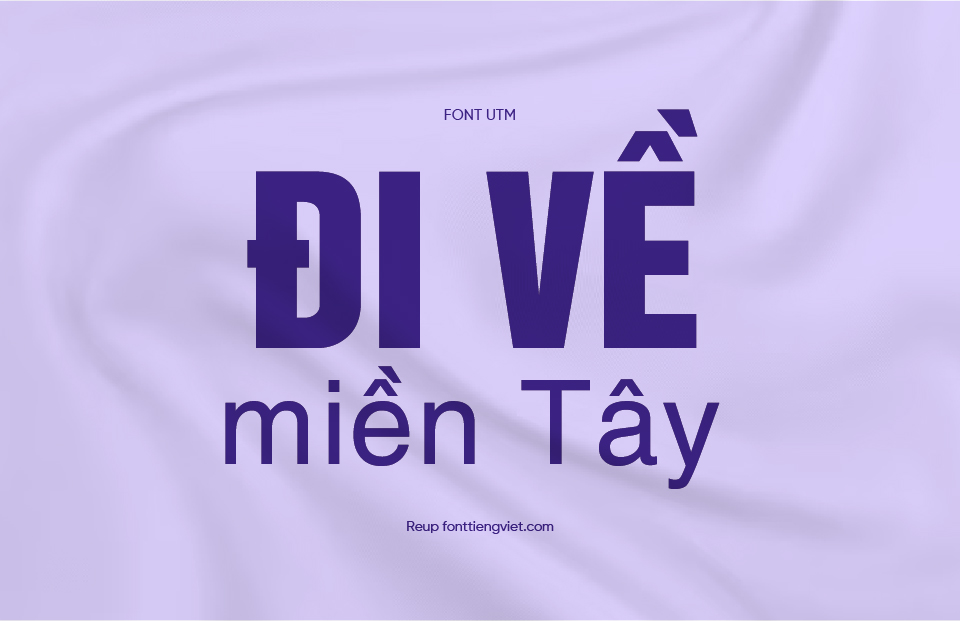
Trong thế giới thiết kế và typography, việc lựa chọn một Font Chữ chất lượng, dễ đọc và chuyên nghiệp luôn là ưu tiên hàng đầu, đặc biệt là đối với các bạn học sinh, sinh viên đang thực hiện đồ án, báo cáo hoặc chuẩn bị cho kỳ thi tốt nghiệp. Một trong những bộ font được cộng đồng thiết kế Việt Nam tin dùng nhất chính là Font Việt hóa UTM Helve. Đây không chỉ là một phông chữ đẹp mà còn là giải pháp hoàn hảo cho mọi nhu cầu hiển thị tiếng Việt.
Bộ font này đã được tối ưu hóa để tương thích tuyệt đối với các dấu tiếng Việt, tránh lỗi nhảy chữ hay mất nét, giúp tài liệu của bạn luôn giữ được sự chuyên nghiệp và chỉn chu. Nếu bạn đang tìm kiếm sự kết hợp giữa nét hiện đại, tối giản của Helvetica với sự tinh tế của tiếng Việt, thì Font Việt hóa UTM Helve chính là câu trả lời không thể bỏ qua cho các dự án thiết kế đồ họa và học thuật.
UTM Helve – Sự Lựa Chọn Hoàn Hảo Cho Thiết Kế Đồ Án Học Thuật
Đối với học sinh cấp 3 hay sinh viên đại học, việc trình bày các bài luận, slide thuyết trình hay đồ án tốt nghiệp đóng vai trò quan trọng trong việc đánh giá kết quả. Sự rõ ràng, dễ đọc của văn bản sẽ ảnh hưởng trực tiếp đến trải nghiệm của người chấm. Bộ UTM Helve ra đời để giải quyết triệt để vấn đề này, mang lại sự chuyên nghiệp tức thì cho bất kỳ tài liệu nào.
Với thiết kế dựa trên nguyên tắc tối giản (minimalism) và tính khoa học, UTM Helve mang lại cảm giác sạch sẽ, hiện đại, phù hợp với hầu hết các phong cách thiết kế từ nghiêm túc, học thuật đến sáng tạo, nghệ thuật. Phong cách Sans Serif kinh điển của nó đảm bảo độ rõ nét ngay cả ở kích thước nhỏ. Sự đa dạng về trọng lượng (weights) từ Light, Regular đến Bold giúp người dùng dễ dàng tạo ra sự phân cấp thông tin rõ ràng trong tài liệu của mình, từ tiêu đề chính cho đến phần chú thích nhỏ.
Việc sử dụng một bộ font chuẩn mực như UTM Helve còn thể hiện sự nghiêm túc và đầu tư của người làm đồ án. Đây là lý do tại sao nhiều giảng viên và chuyên gia thiết kế luôn khuyến khích sử dụng các dòng font chất lượng cao như bộ font UTM, đặc biệt là phiên bản UTM Helve đã được Việt hóa hoàn chỉnh.
Font Việt hóa UTM Helve: Tại Sao Lại Được Ưa Chuộng Đến Vậy?
Đặc điểm nổi bật của dòng UTM Helve
Sức hút của bộ font này không chỉ đến từ vẻ ngoài mà còn nằm ở khả năng tương thích tiếng Việt hoàn hảo. Quá trình Việt hóa đã được thực hiện tỉ mỉ bởi các chuyên gia, đảm bảo mọi ký tự có dấu, đặc biệt là các tổ hợp dấu phức tạp như ‘ễ’, ‘ữ’, ‘ở’ đều hiển thị mượt mà, không bị lỗi căn chỉnh hay vỡ nét. Đây là lợi thế lớn so với các font quốc tế chưa được tối ưu hóa đầy đủ cho ngôn ngữ tiếng Việt.
Sự chú trọng vào tính năng việt hóa giúp Font Việt hóa UTM Helve trở thành công cụ không thể thiếu khi bạn cần xuất bản tài liệu tiếng Việt chất lượng cao. Các nhà thiết kế chuyên nghiệp thường dùng nó cho branding, UI/UX, và tất nhiên, nó cực kỳ hữu ích cho các bài báo cáo khoa học của sinh viên, đảm bảo sự truyền tải thông tin không bị gián đoạn bởi các lỗi kỹ thuật về font chữ.
Ứng dụng trong môi trường học thuật và thi cử
Dù là soạn thảo tài liệu ôn thi tốt nghiệp THPT, chuẩn bị hồ sơ du học, hay chỉ đơn giản là viết một bài báo cáo thực tập, UTM Helve luôn đảm bảo tính thẩm mỹ và dễ đọc. Tính nhất quán của font chữ giúp người đọc tập trung vào nội dung mà không bị phân tâm bởi lỗi font hay kiểu chữ rườm rà. Điều này đặc biệt quan trọng trong các tài liệu cần sự nghiêm túc và chính xác cao, nơi mà sự dễ đọc là yếu tố then chốt.
Các bạn học sinh chuẩn bị cho kỳ thi tốt nghiệp có thể sử dụng font này để thiết kế các bảng tổng hợp kiến thức hoặc mindmap, đảm bảo các tài liệu in ấn ra luôn sắc nét và rõ ràng. Đối với sinh viên, việc sử dụng Font Việt hóa UTM Helve trong các slide thuyết trình (presentation slides) cũng giúp thông điệp truyền tải đến người nghe một cách hiệu quả và chuyên nghiệp hơn.
Tóm lại, Font Việt hóa UTM Helve là một tài sản quý giá cho bất kỳ ai hoạt động trong lĩnh vực thiết kế, học thuật, hoặc cần một bộ Font Chữ đẹp và chuyên nghiệp để nâng cao chất lượng tài liệu. Sự kết hợp giữa tính hiện đại, khả năng đọc tuyệt vời và tính năng Việt hóa hoàn hảo đã giúp nó trở thành một trong những font được tải về nhiều nhất. Đừng chần chừ, hãy tải ngay bộ font này để biến các bài báo cáo, đồ án hay tài liệu ôn thi tốt nghiệp của bạn trở nên ấn tượng và chuyên nghiệp hơn bao giờ hết!